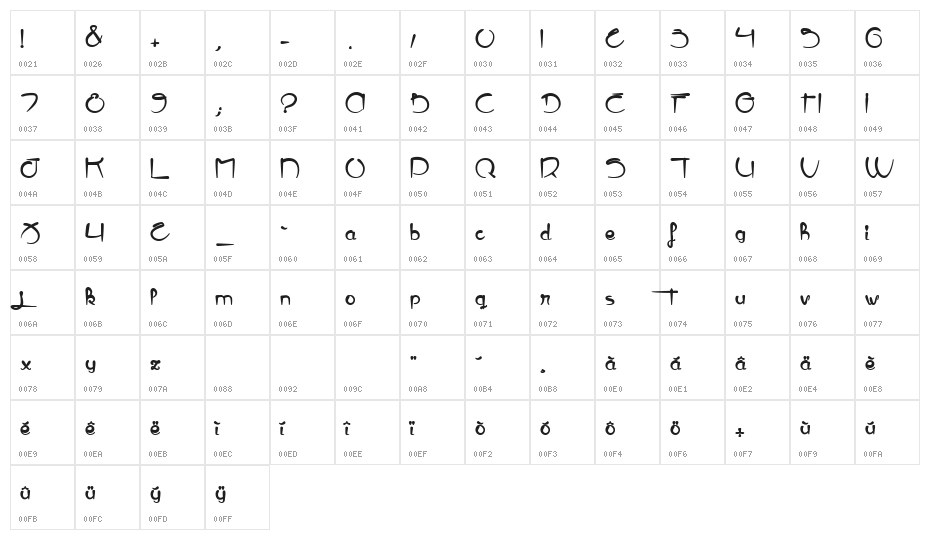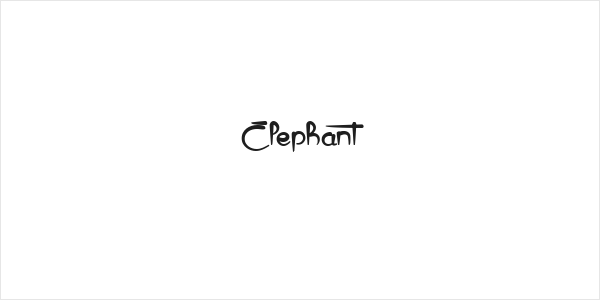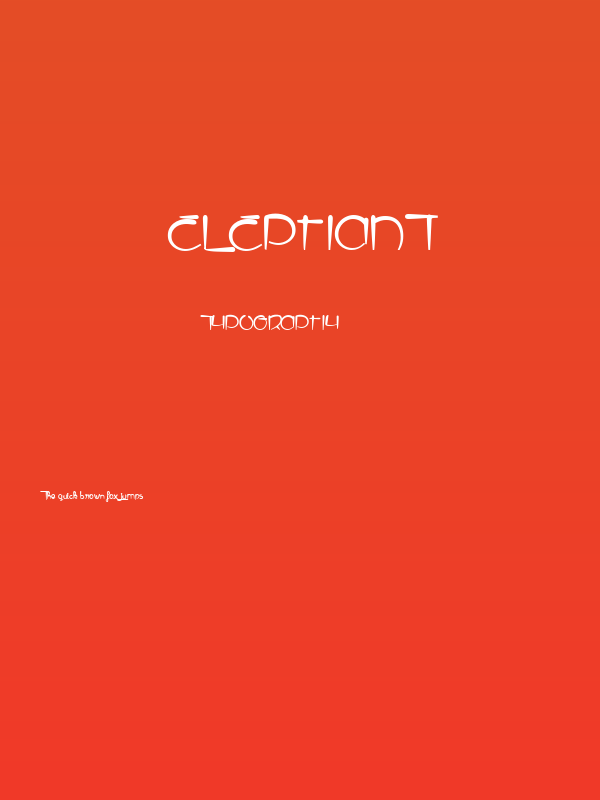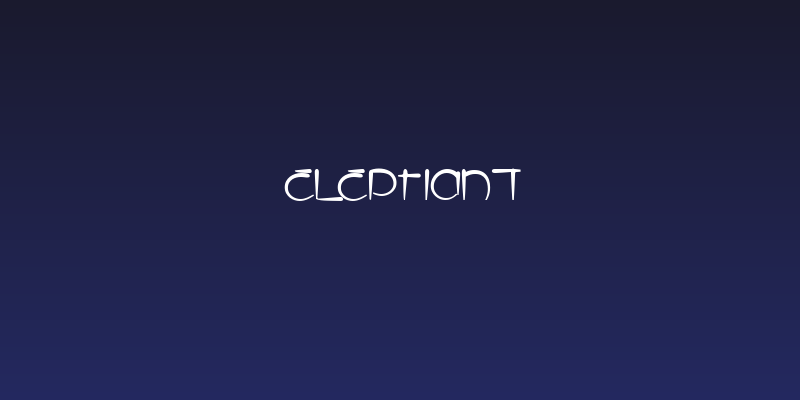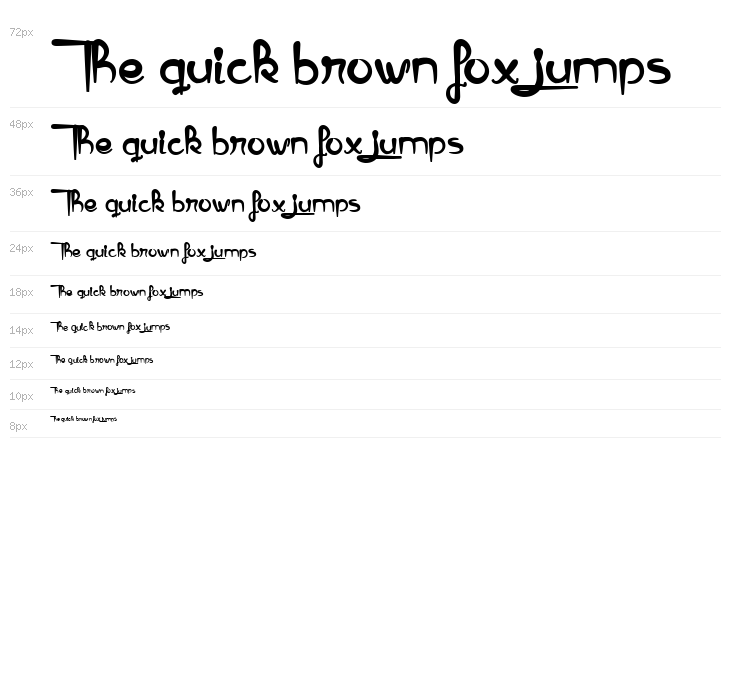
Elephant Font
| Gesamtstil | Modern, Artistic |
| Vorgeschlagene Projekte | Ideal for children's book covers, playful branding, creative posters, and artistic invitations. |